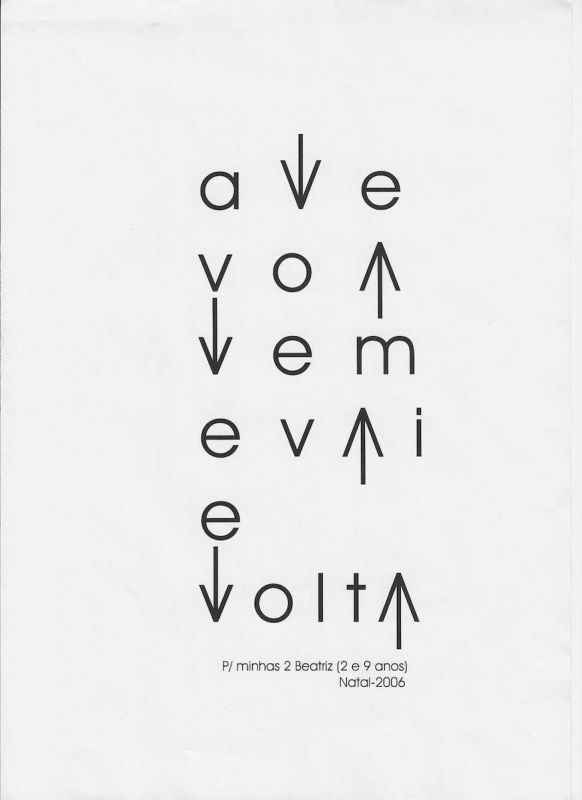
Ave Voa Vem e Vai e Volta é uma impressão gráfica de Avelino de Araújo realizada em Natal em 2006, vinculada à poesia visual, à poesia experimental, à arte conceitual, à tipografia e às investigações intersígnicas associadas ao campo do Poema Processo.
Ave Voa Vem e Vai e Volta é uma impressão gráfica de Avelino de Araújo realizada em Natal em 2006, vinculada à poesia visual, à poesia experimental, à arte conceitual, à tipografia e às investigações intersígnicas associadas ao campo do Poema Processo. A composição distribui as palavras ave, voa, vem, e, vai e volta em uma estrutura vertical construída com letras minúsculas, espaços amplos e sinais direcionais. Setas orientadas para cima e para baixo são incorporadas às palavras e ocupam o lugar de letras ou prolongam suas formas, fazendo com que escrita, movimento e imagem funcionem simultaneamente. O poema não apresenta apenas uma frase sobre o deslocamento de uma ave. Sua própria organização gráfica executa ações de subida, descida, aproximação, afastamento, partida e retorno. As letras a e v estabelecem relações formais com as pontas das setas, permitindo que caracteres tipográficos sejam convertidos em indicadores de direção. A sequência ave voa vem e vai e volta produz ritmo por meio da repetição das letras a, v, e e o e pela alternância de verbos que descrevem movimentos opostos e complementares. Voar, vir, ir e voltar formam um ciclo de deslocamento e retorno que pode ser associado à liberdade, à viagem, ao crescimento, à ausência, ao reencontro, à memória e à permanência dos vínculos afetivos. O amplo espaço branco ao redor das palavras reforça a sensação de céu, distância e circulação. A leitura ocorre de cima para baixo, mas as setas interrompem essa direção única e convidam o observador a percorrer a página nos dois sentidos. A obra transforma uma construção verbal simples em partitura visual e coreografia tipográfica. Na região inferior encontra se a dedicatória P minhas 2 Beatriz, com a indicação das idades 2 e 9 anos, seguida por Natal 2006. A informação registra o caráter afetivo e pessoal da peça e sugere uma homenagem a duas pessoas chamadas Beatriz. Ave Voa Vem e Vai e Volta integra a produção de Avelino de Araújo baseada na economia de elementos, na transformação da palavra em imagem, no uso de sinais gráficos e na participação perceptiva do leitor. Palavras chave para indexação: Avelino de Araújo, Ave Voa Vem e Vai e Volta, 2006, Natal, impressão gráfica, poesia visual brasileira, poema visual, poesia experimental, arte conceitual, Poema Processo, ave, voo, movimento, partida, retorno, setas, direção, tipografia experimental, palavra imagem, texto imagem, leitura multidirecional, semiótica, intersigno, comunicação visual, dedicatória a Beatriz, arte gráfica brasileira, múltiplo gráfico, arquivo de poesia visual, arte brasileira do século vinte e um.TEXT FOR THE SALSA PROGRAM IN ENGLISH: Bird Flies Comes and Goes and Returns is a graphic print by Avelino de Araújo produced in Natal in 2006 and associated with visual poetry, experimental poetry, conceptual art, typography and intersemiotic investigations connected with the field of the Poema Processo movement. The composition distributes the Portuguese words ave, voa, vem, e, vai and volta in a vertical structure constructed with lowercase letters, broad spaces and directional signs. Upward and downward arrows are incorporated into the words and replace letters or extend their forms, allowing writing, movement and image to operate simultaneously. The poem does not merely present a sentence about the movement of a bird. Its graphic organization performs actions of ascent, descent, approach, departure and return. The letters a and v establish formal relationships with the pointed shapes of the arrows, enabling typographic characters to become indicators of direction. The sequence ave voa vem e vai e volta creates rhythm through the repetition of the letters a, v, e and o and through the alternation of verbs describing opposite and complementary movements. Flying, coming, going and returning form a cycle that may be associated with freedom, travel, growth, absence, reunion, memory and the continuity of emotional bonds. The extensive white space surrounding the words strengthens the sensation of sky, distance and circulation. Reading proceeds from top to bottom, but the arrows interrupt this single direction and invite the viewer to move across the page in both directions. The work transforms a simple verbal construction into a visual score and typographic choreography. The lower region contains the dedication P minhas 2 Beatriz, referring to two people named Beatriz and indicating the ages of 2 and 9 years, followed by Natal 2006. This information records the personal and emotional character of the piece. Bird Flies Comes and Goes and Returns belongs to Avelino de Araújo
Impressão gráfica em tinta preta sobre papel claro, composta por letras minúsculas e setas distribuídas verticalmente na região central da folha. A composição permite reconhecer a sequência ave, voa, vem, e, vai e volta. Algumas letras são substituídas ou prolongadas por setas verticais orientadas para cima e para baixo. Os sinais direcionais apresentam hastes finas e pontas formadas por linhas diagonais, estabelecendo semelhança visual com as letras a e v. As palavras aparecem separadas em linhas e com espaçamento amplo, criando uma leitura fragmentada, rítmica e multidirecional. A maior parte da folha permanece sem impressão, reforçando a leveza e o isolamento dos elementos gráficos. Na parte inferior aparece a dedicatória P minhas 2 Beatriz, acompanhada pela indicação 2 e 9 anos, e abaixo encontra se a inscrição Natal 2006. O suporte apresenta leves ondulações, vincos, marcas de dobra e discretos sinais de manuseio. A peça pode ser classificada como poema visual, impressão de artista, múltiplo gráfico, estudo tipográfico, dedicatória afetiva e documento conceitual, sendo relevante para pesquisas sobre Avelino de Araújo, Poema Processo, poesia visual, movimento, voo, setas, linguagem, tipografia, semiótica e produção gráfica brasileira.OBSERVATION TEXT IN ENGLISH: Graphic print in black ink on light colored paper composed of lowercase letters and arrows arranged vertically in the central region of the sheet. The composition allows recognition of the Portuguese sequence ave, voa, vem, e, vai and volta. Some letters are replaced or extended by vertical arrows pointing upward and downward. The directional signs have thin stems and pointed ends formed by diagonal lines, creating a visual resemblance to the letters a and v. The words are divided across separate lines with broad spacing, producing fragmented, rhythmic and multidirectional reading. Most of the sheet remains unprinted, reinforcing the lightness and isolation of the graphic elements. The lower section contains the dedication P minhas 2 Beatriz, accompanied by the indication 2 e 9 anos, meaning 2 and 9 years, with Natal 2006 printed below. The support presents slight undulations, creases, fold marks and minor traces of handling. The piece may be classified as a visual poem, artist print, graphic multiple, typographic study, emotional dedication and conceptual document, making it relevant to research on Avelino de Araújo, Poema Processo, visual poetry, movement, flight, arrows, language, typography, semiotics and Brazilian graphic production.
Bird Flies Comes and Goes and Returns is a graphic print by Avelino de Araújo produced in Natal in 2006 and associated with visual poetry, experimental poetry, conceptual art, typography and intersemiotic investigations connected with the field of the Poema Processo movement.